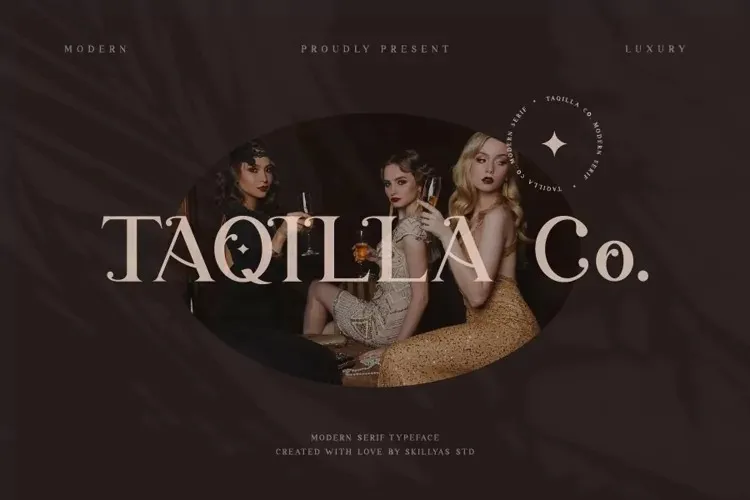
A Taqilla Co é uma fonte serif que traz elegância e luxo a qualquer projeto. Desenvolvida para transparecer feminilidade e glamour, mas também oferecendo beleza com muitas alternativas e opções de ligação para criar inúmeras variações atendendo às suas necessidades criativas. Ideal para uma variedade de usos, ela se destaca em campos como fotografia, marca impressa, design gráfico, embalagens, eventos especiais ou qualquer lugar onde você deseja adicionar um toque sofisticado e elegante ao seu trabalho. A Taqilla Co é perfeita para quem busca criar um design com unção e coerência, uma vez que permite a criação de variadas opções visuais através de seus ajustes sutis e detalhes finos.